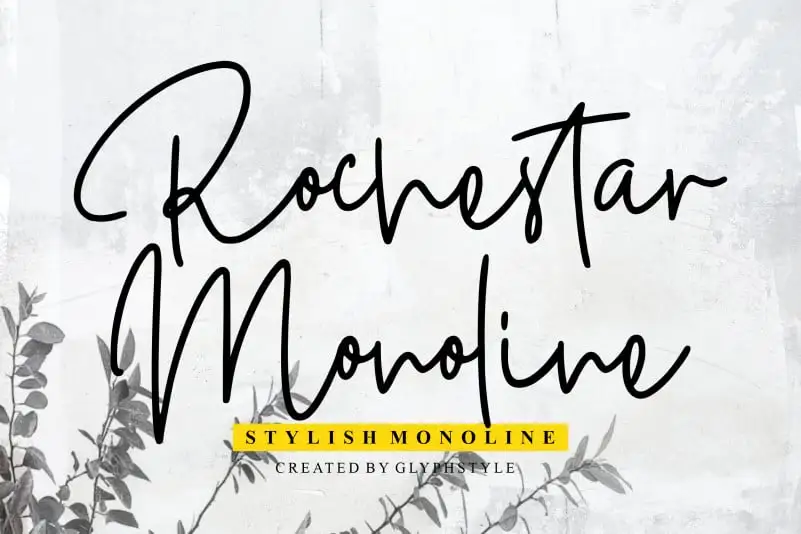
Rochestar Stylish Handwritten Font – Fonte Grátis
Rochestar Stylish Handwritten Font
A Rochestar Stylish Handwritten Font é uma elegante escolha para quem busca uma fonte que transmite sofisticação com autenticidade. Com seu estilo monolíneo e escrita a mão, este tipo proporciona um tom suave e versátil, adequado para diversos usos, desde logotipos de entrevistas até cartões de convite e logos de produtos. Seu design simples e elegante o torna perfeito para criar visuais impactantes e atemporais que se destacam em qualquer plataforma de comunicação digital ou impressão. A Rochestar Stylish Handwritten Font é uma excelente opção para quem busca um equilíbrio entre simplicidade e sofisticação, garantindo um toque único em seu trabalho. Não importa qual projeto você esteja trabalhando, esta fonte vai oferecer a perfeição que você precisa.